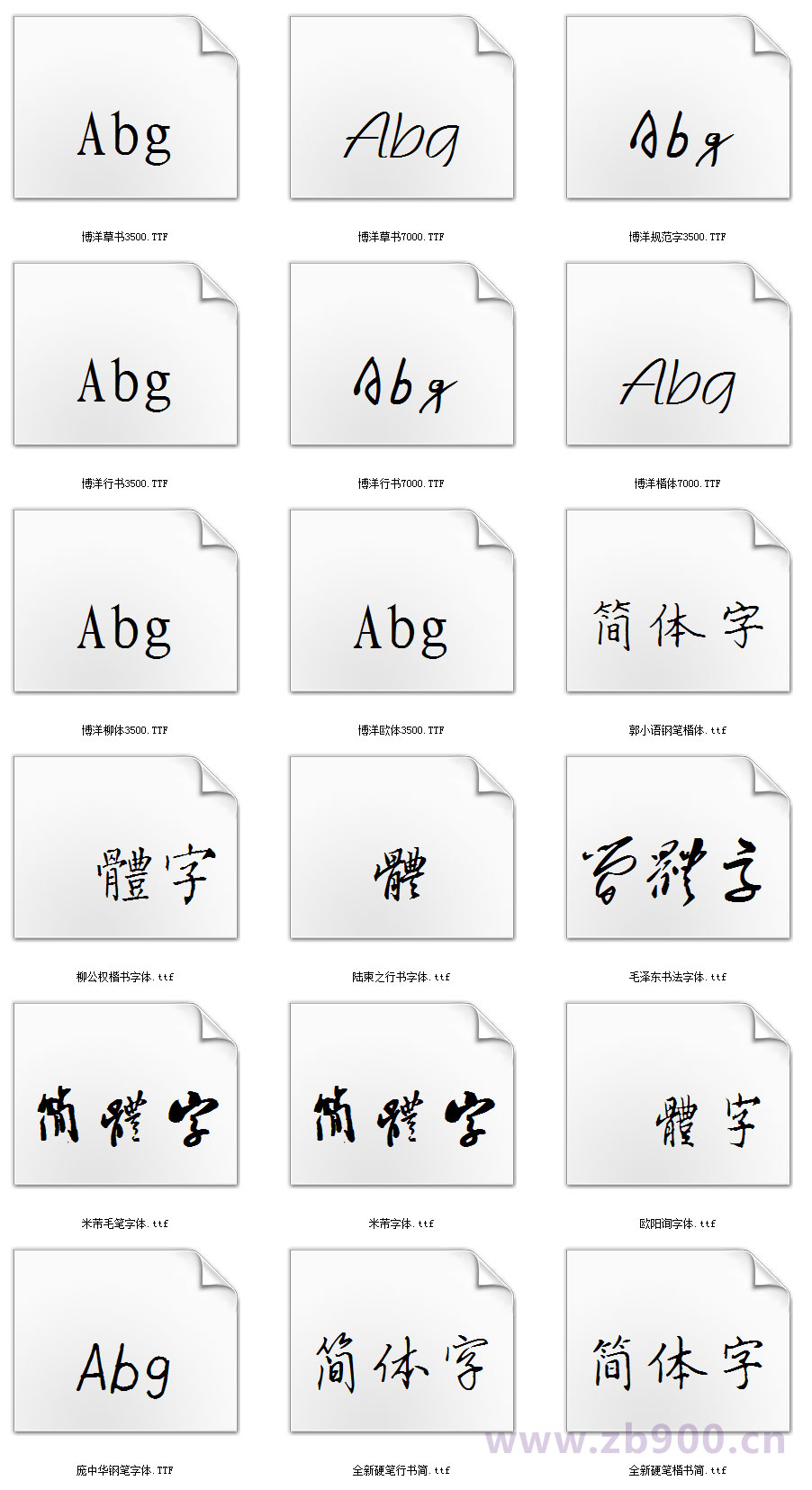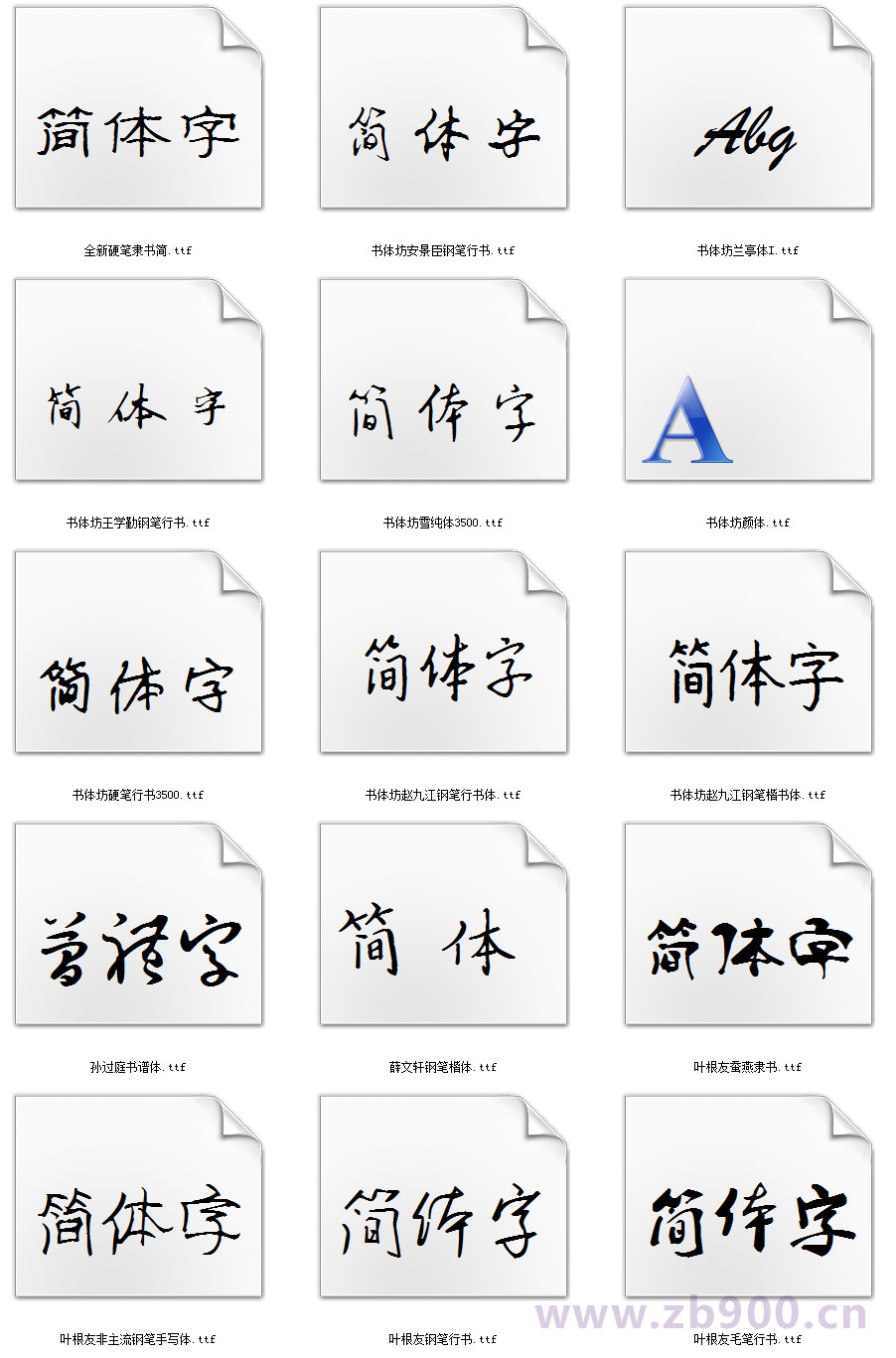
字体特性
支持“欧阳询”“坊兰亭”“赵九江”“叶根友”“柳公权”等众多书法名家的书法字体。
虽然都是按古人书法仿造的字体,但利用电脑先进的字体设计功能,已经和原版没什么区别了,使用的时候做好一定的排版和大小调整。
博洋柳体3500
米芾毛笔字体
书体坊安景臣钢笔行书
书体坊赵九江钢笔楷书体
智永行书字体